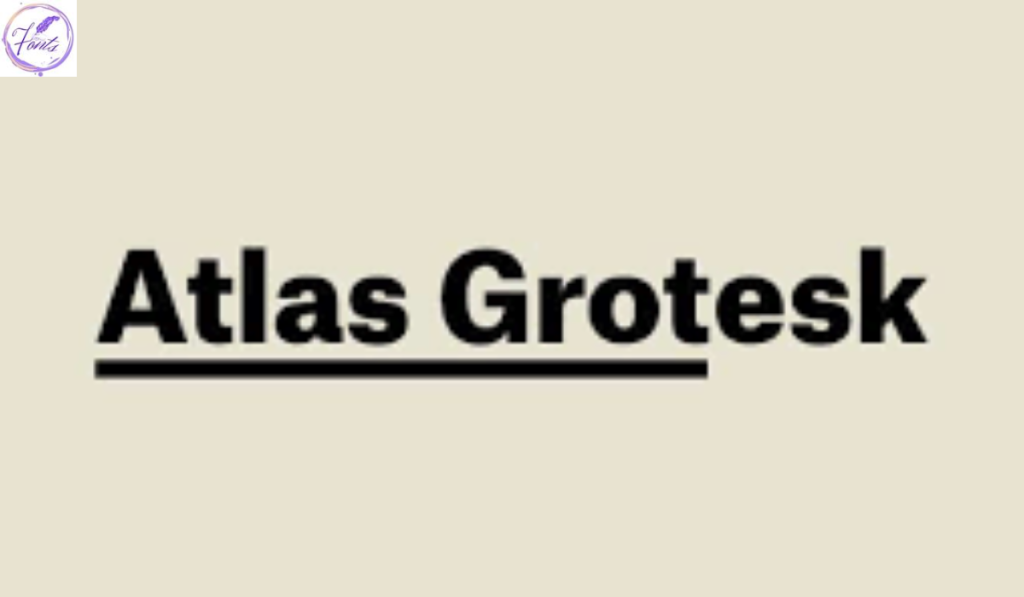
Atlas Grotesk font family việt hóa
Tác giả: Susana Carvalho, Kai Bernau, Christian Schwartz
Ngày phát hành: 2010
Ngôn ngữ: Tiếng Việt, Tiếng Anh, và nhiều ngôn ngữ khác
Bộ Font: Atlas Grotesk
Phân loại: cá tính, độc đáo, hiện đại
Kiểu chữ: sans serif
Độ dày: Thin, ExtraLight, Light, Regular, Medium, SemiBold, Bold, ExtraBold, Black
Atlas grotesk font family là một bộ font sans-serif đa năng và hiện đại, được thiết kế bởi bộ ba nhà thiết kế tài năng lần lượt là Susana Carvalho, Kai Bernau, Christian Schwartz. Font atlas grotesk font family được xuất bản bởi Commercial Type vào năm 2010 gây nên ấn tượng lớn với dân thiết kế đồ họa lúc bấy giờ. Với 7 kiểu chữ và 42 font khác nhau, atlas grotesk font family mang đến sự linh hoạt và phong phú cho mọi dự án thiết kế. Bộ font lấy cảm hứng từ những phông chữ sans-serif cổ điển của thế kỷ 20, nhưng được cải tiến với các chi tiết tinh tế và tỷ lệ cân đối, tạo nên một diện mạo mới mẻ, thanh lịch và dễ đọc.
Đánh giá atlas grotesk font family
Atlas grotesk font family sở hữu nhiều ưu điểm vượt trội. Các nét chữ rõ ràng, sắc nét, kết hợp với khoảng cách chữ hợp lý giúp tối ưu hóa trải nghiệm đọc trên mọi phương tiện, từ in ấn đến hiển thị màn hình. Atlas grotesk regular font free download và các phiên bản khác trong bộ font đều hỗ trợ hơn 200 ngôn ngữ Latin mở rộng, đáp ứng nhu cầu sử dụng đa dạng của người dùng trên toàn thế giới.
Trong cuộc thi “Typeface Design Competition 2013” do TDC (Type Directors Club) tổ chức, atlas grotesk font family đã vinh dự giành giải Vàng ở hạng mục “Typeface Family”. Nhiều thương hiệu và tổ chức nổi tiếng như Apple, Google, BBC, và Nike đã tin tưởng lựa chọn atlas grotesk cho các ấn phẩm và sản phẩm của mình.